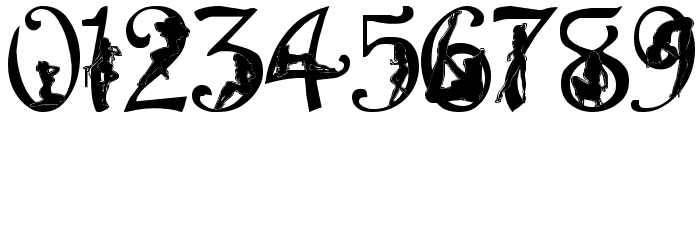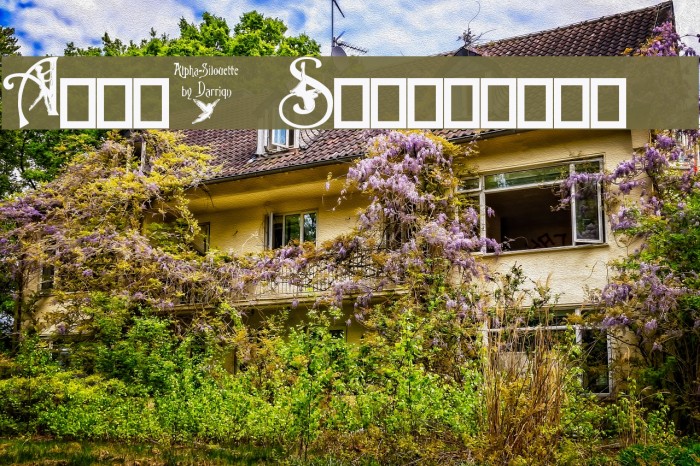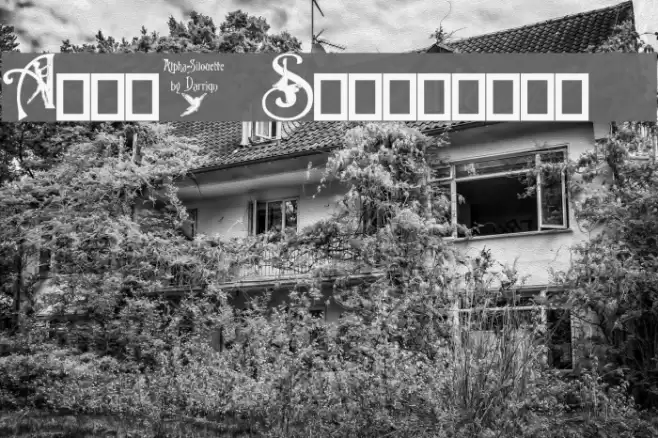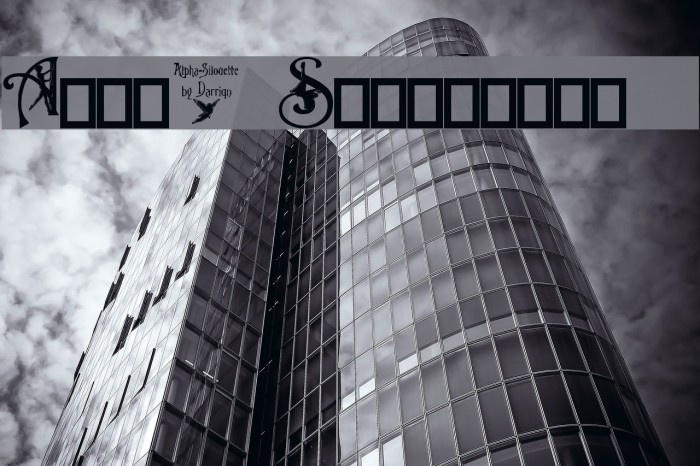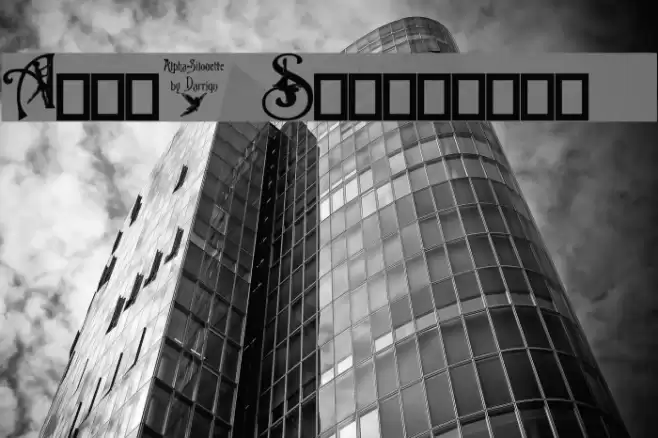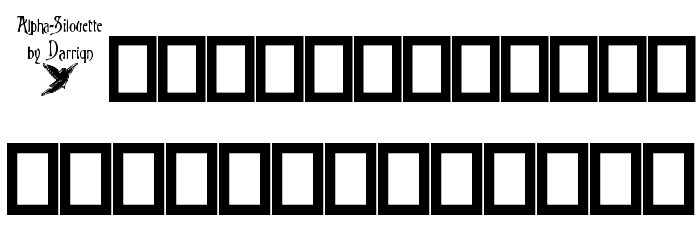
Alpha-Silouette Font
| Caso d'uso | Logos, Headlines, Artistic projects |
| Progetti proposti | Ideal for fantasy-themed posters, book covers, greeting cards, and artistic projects requiring a whimsical touch. |